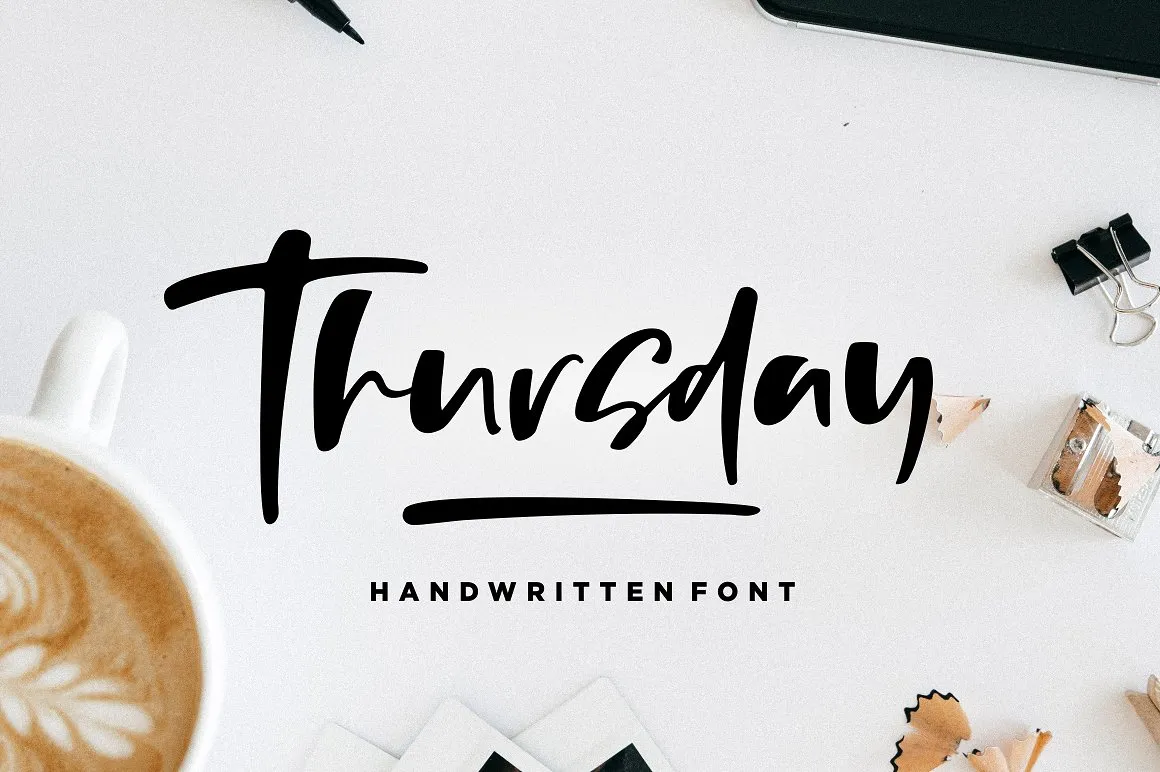
Thursday Vibes Brush Font – Download Grátis
Olá amigos! Aqui está uma nova fonte feita à mão para vocês hoje, lançada pelo designer Sronstudio. Esta é perfeitamente adequada para diversos projetos — desde design gráfico até produtos físicos! A imaginação se multiplica quando pensamos em usá-la. É com prazer que apresentamos a vocês o Thursday Vibes Brush Font. Thursday Vibes Brush Font é perfeito tanto para logos e marcas, como para convites, material de papelaria, designs de casamentos, postagens nas redes sociais, anúncios, embalagem dos produtos, design dos produtos, etiquetas, fotografia e até mesmo como marca d’água. É uma ótima escolha para qualquer evento especial ou simplesmente qualquer uso onde você deseja um toque agradável de personalização à sua criação. Sem dúvida, esta fonte será mais um importante membro da sua colecção que ajudará a dar vida e estilo a tudo o que for criado. Então, se está pronto para mergulhar neste mundo colorido e cheio de vida que é a design visual, então o Thursday Vibes Brush Font está aqui para ajudar!